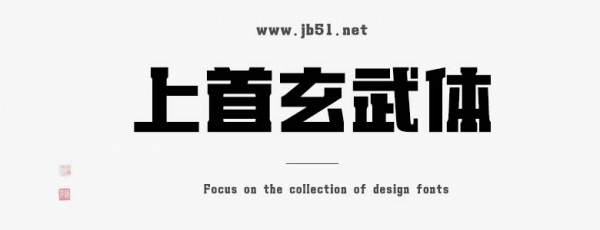
上首玄武體是由上首造字字庫(kù)出品的字體,這款字體筆畫的輪廓由直線和弧線構(gòu)成,筆形厚重,適合應(yīng)用于藝術(shù)設(shè)計(jì)、平面宣傳設(shè)計(jì)、網(wǎng)頁(yè)設(shè)計(jì),書法字帖等領(lǐng)域,需要的朋友可以前來本站下載。
上首玄武體,簡(jiǎn)體中文約6763字,筆畫的輪廓由直線和弧線構(gòu)成,筆形厚重,部分折筆處的圓弧角讓字體多了一絲圓潤(rùn),方圓交融,看上去顯得迅捷流暢。字體嚴(yán)謹(jǐn)?shù)臉?gòu)體使視覺明快,實(shí)用且美觀。